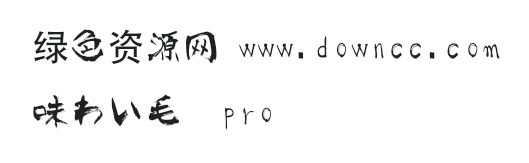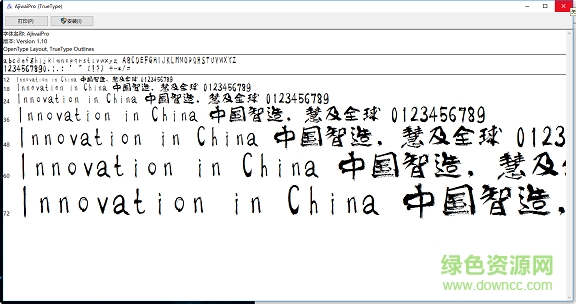
軟件介紹 軟件標簽: 毛筆字體 字體 味わい毛筆pro是一款敲可愛的毛筆字體。小編在網(wǎng)上苦苦搜羅了好久在找到呢~歡迎大家來下載華康寶風體簡軟件介紹今天小編為你帶來味わい毛筆pro字體。味わい毛筆pro看著圓滑,看上去萌萌噠,非常適合廣告設計、平面設計、印刷包裝、正文標題等人員使用。味わい毛筆pro安裝說明方法一:控制面板/字體/文件/安裝新字體方法二:直接將字體復制到C:\WINDOWS\Fonts方法三:針對win7系統(tǒng),用戶只需選中字體右鍵安裝即可華康寶風體簡體小編點評味わい毛筆pro是一款特別日式風格的字體~ 軟件截圖 上一張下一張(1 / 1) 安裝詳細截圖 猜你喜歡 毛筆字體 毛筆字體 毛筆字體是一類同硬筆書法完全不同的書寫方式,毛筆方法種類繁多更顯飄逸與古典氣質(zhì),是中國人的經(jīng)典傳承,無論是用于對聯(lián)、藝術設計還是門匾都顯示深沉莊重,綠色資源網(wǎng)小編整理了毛筆書法字體大全,歡迎大家下載體驗! 查看更多>> plume毛筆字體 416KB/中文/10.0/下載 衡山毛筆行書 4.16M/中文/10.0/下載 金梅新毛筆草楷 3.41M/中文/10.0/下載 金梅新毛筆隸書 2.34M/中文/10.0/下載 味わい毛筆pro字體 35.00M/中文/6.0/下載 葉根友毛筆行書2.0版 1.09M/中文/1.7/免費版下載 其他版本下載 標題 大小 更新日期 下載 下載地址 電腦版 味わい毛筆pro字體 點擊報錯 軟件無法下載或下載后無法使用,請點擊報錯,謝謝! 關閉報錯反饋 請描述您所遇到的錯誤,我們將盡快予以修正,謝謝! *必填項,請輸入內(nèi)容 本類最新 dreamweaver字體庫 首爾南山體字體 v1.06 官方版 潮字社風云簡ttf 潮字社凌渡鯤鵬簡體字體 潮字社曾玉波手書簡字體 微博慧心字體 相關文章 Photoshop字體安裝使用方法和技巧 如何解決“無法新增字體”問題 Win 7系統(tǒng)安裝字體方法 網(wǎng)頁字體大小設置方法 怎么改網(wǎng)頁字體大小 在Linux系統(tǒng)中安裝字體的幾種方法 windows7字體顯示問題:打開某些程序的時候顯示的是亂碼 用戶評論 熱門評論 最新評論 發(fā)表評論 查看所有評論(0) 昵稱: 請不要評論無意義或臟話,我們所有評論會有人工審核. 字數(shù): 0/500 (您的評論需要經(jīng)過審核才能顯示)